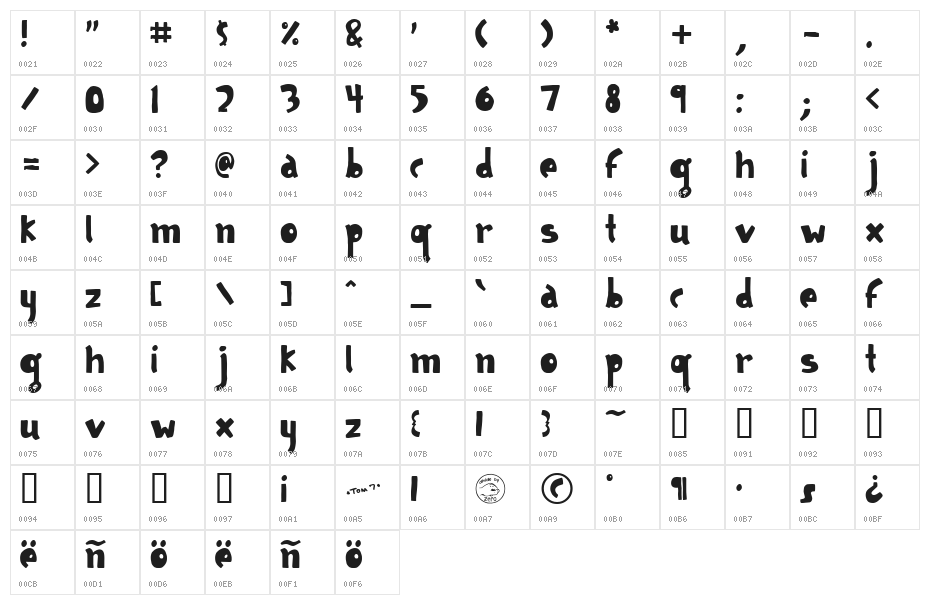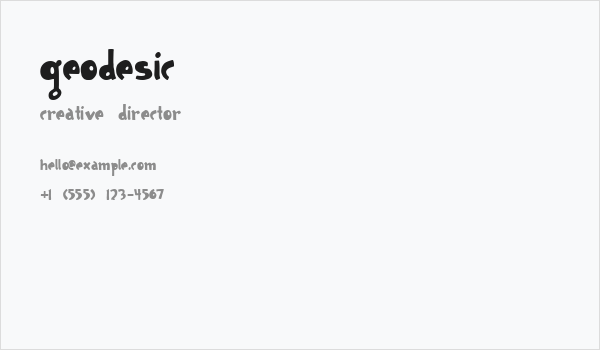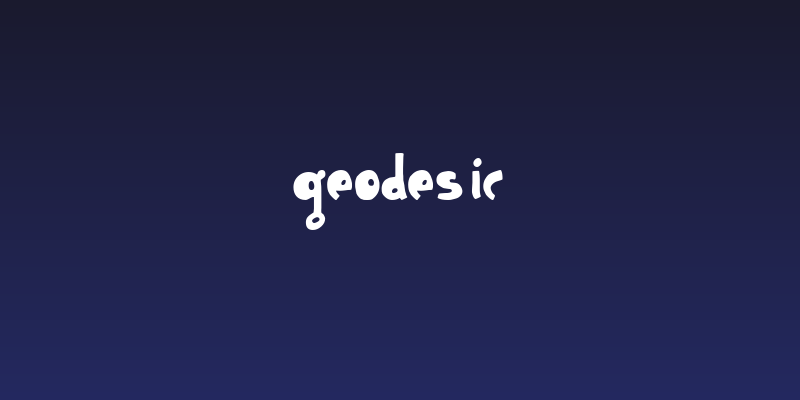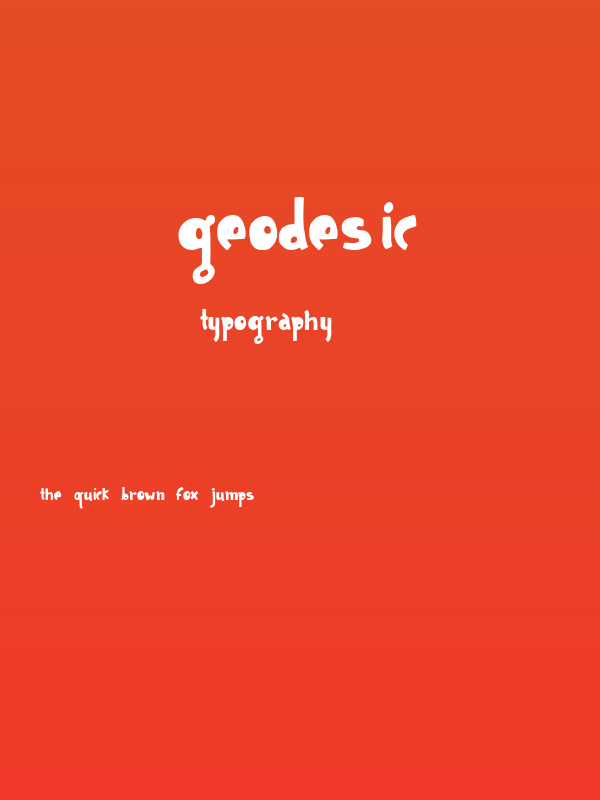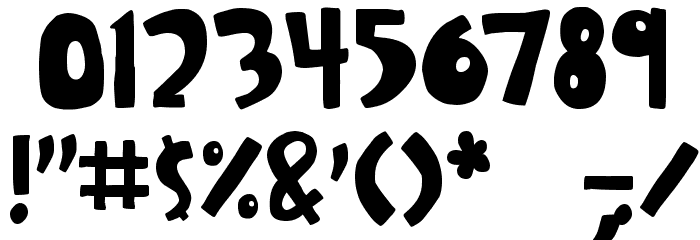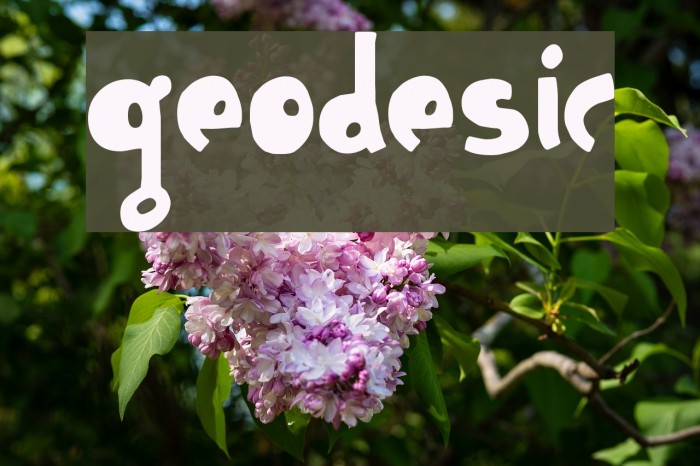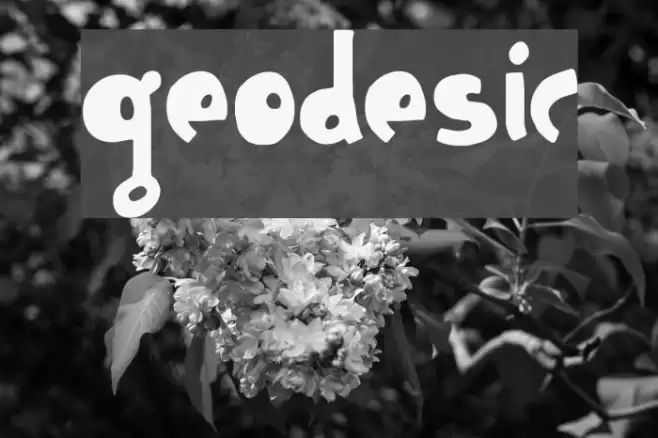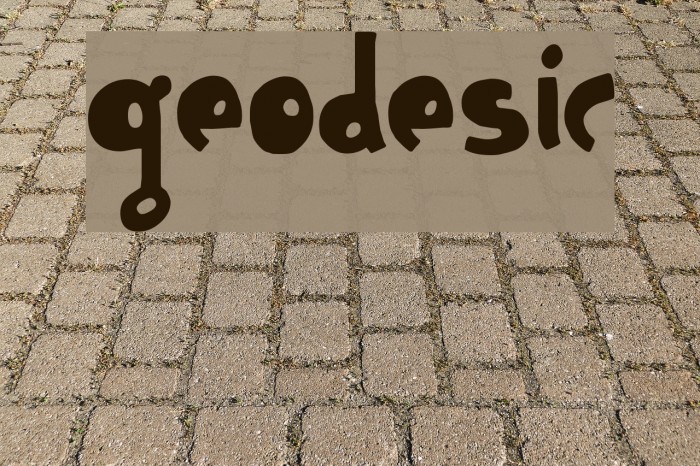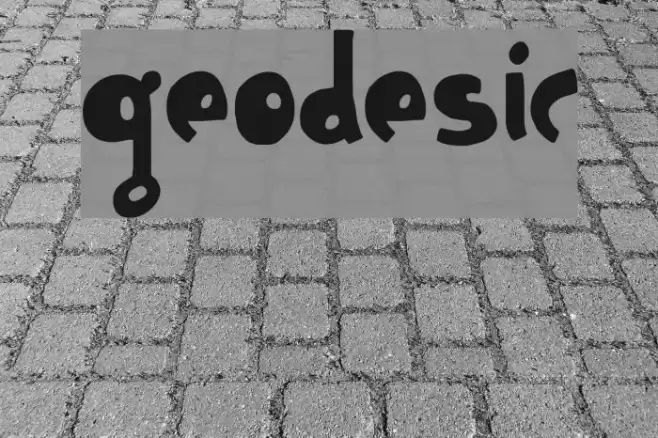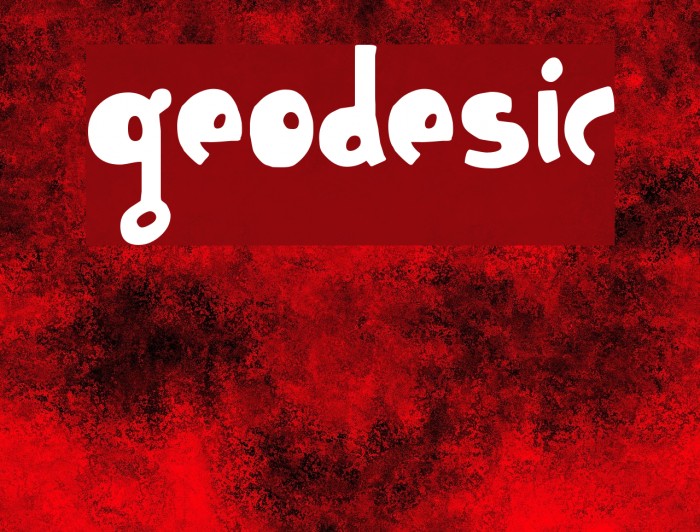
Geodesic Font
| 全体的なスタイル | Playful, Whimsical, Hand-drawn |
| 用途 | Headlines, Posters, Branding |
| おすすめプロジェクト | Ideal for children's books, playful branding, posters, and creative projects that require a fun and engaging typeface. |